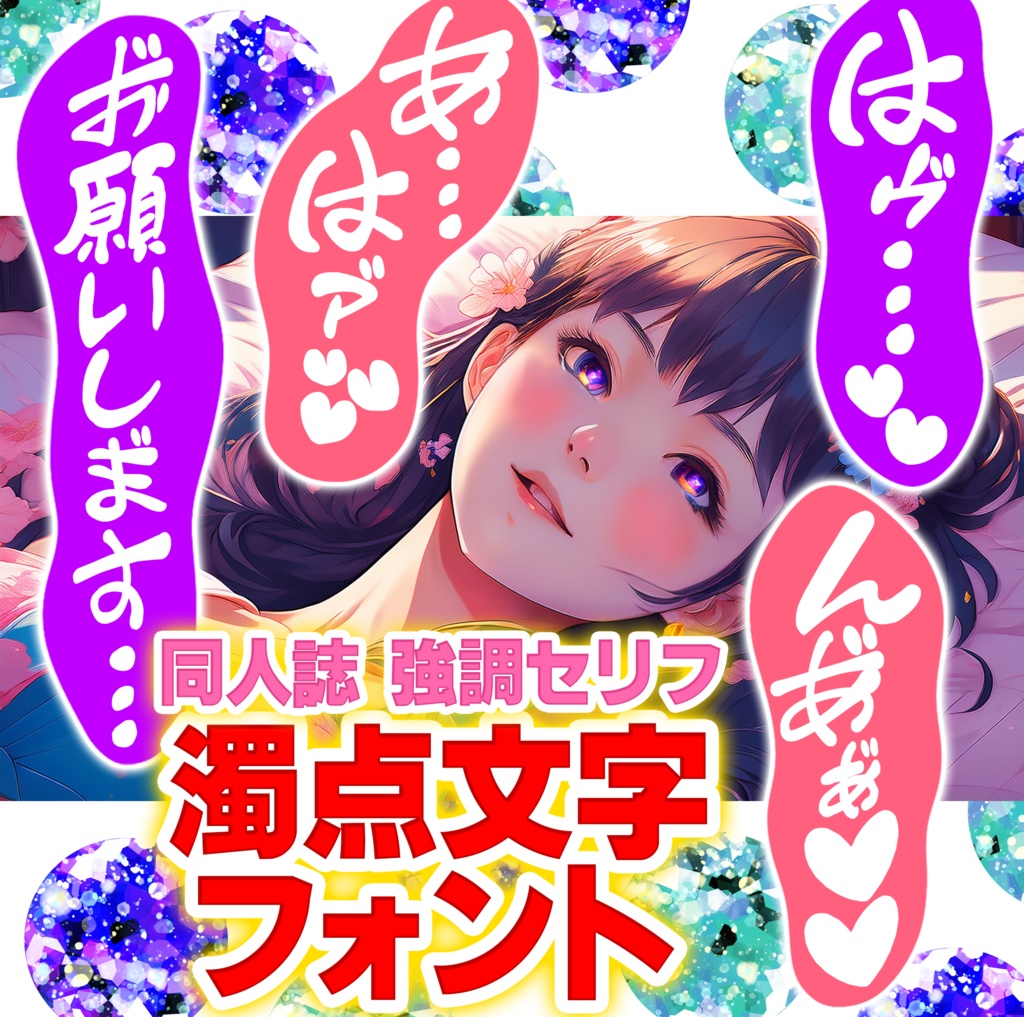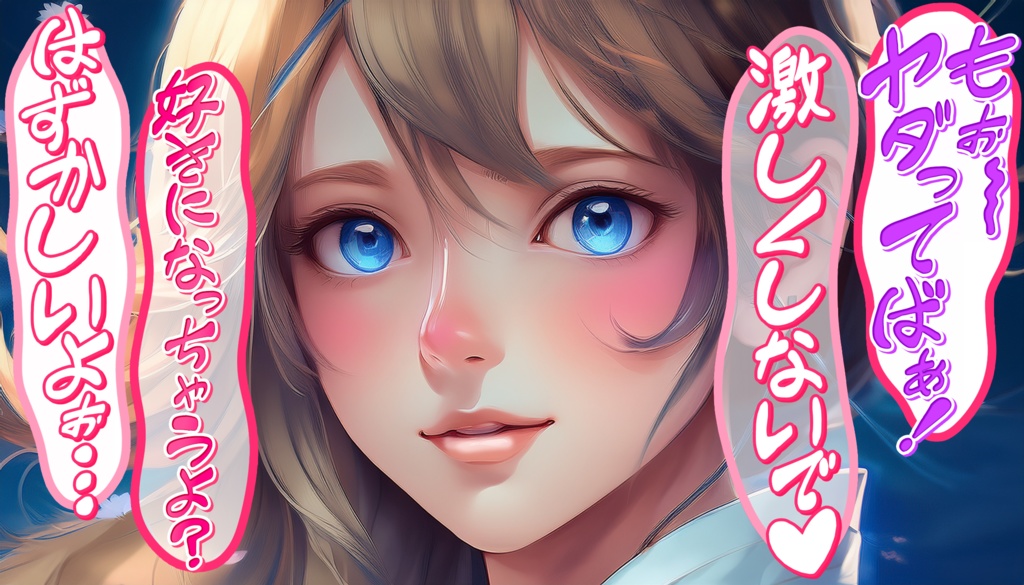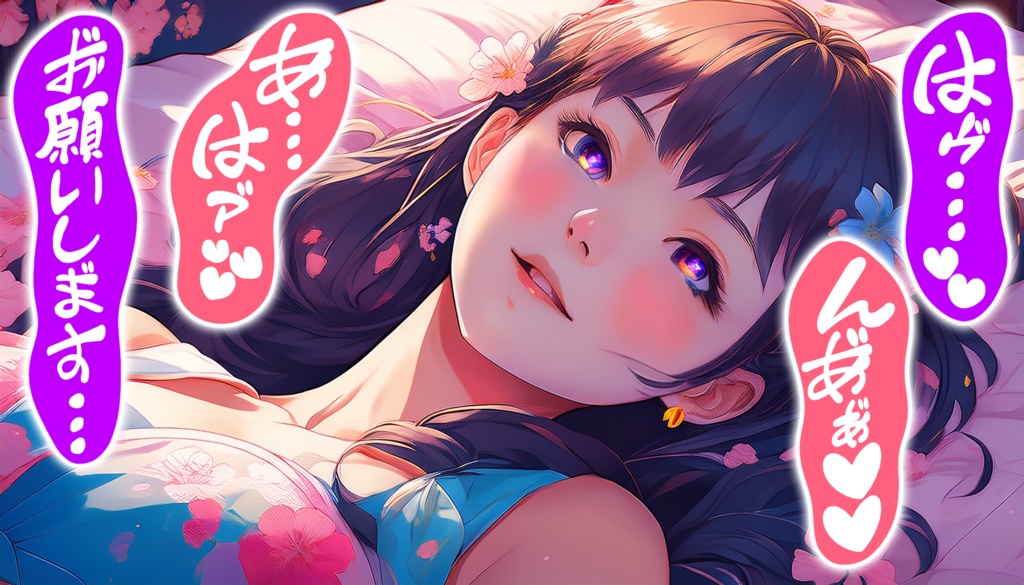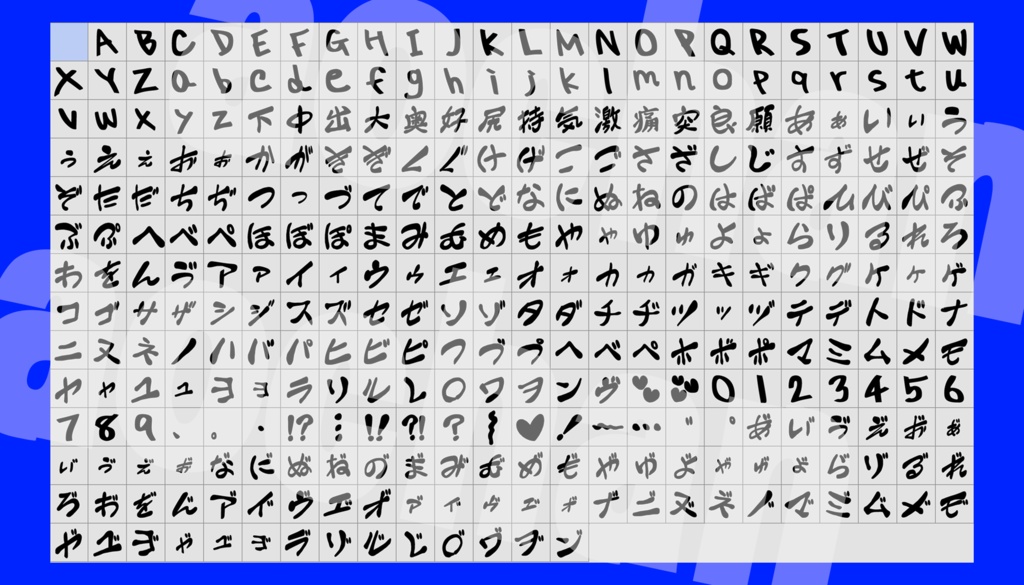
期間限定値下げ中★濁点つけ放題!同人誌 強調セリフ向け手書きフォント『aochan_odorimoji』
12月31日まで期間限定値下げ中! 濁点つけ放題!同人誌 強調セリフ用手書きフォント「aochan_odorimoji」 同人誌や創作漫画で使いやすい、手書き風の日本語フォントです。 特に「強調セリフ」「感情の爆発」「叫び」「崩れた語尾」などの表現に最適! 💥 特徴 通常は濁点が付かない文字にも濁点が付けられる「濁点つけ放題」 (例:「ぁ゛」「あ゛」「ん゛」「ア゛」など) ひらがな・カタカナ・アルファベット(大文字・小文字)・数字を収録 記号(♥ / ♥♥ / !? / !! / 〜 / …など)を収録 漢字は同人誌によく使用されるもののみ収録 収録内容は添付画像が全てです 💡 使用方法 キーボードからは「あ゛」などの濁点付き文字は入力できません。 文字一覧(字形)から選択して使用してください。 Photoshop:メニュー → ウィンドウ → 字形 から文字を選択 Illustrator:メニュー → 書式 → 字形 または ウィンドウ → 書式 → 字形 CLIP STUDIO PAINT(クリスタ):文字パレットを使用してください ✏ 収録内容 ひらがな・カタカナ アルファベット(大文字・小文字) 数字 記号(♥/ !? / ?! / !! / 〜 / …など) 漢字(同人誌によく使用されるもの) 濁点付き文字(あ゛・ん゛・ア゛など) 💼 商用利用について 個人・同人・商用利用すべてOK 再配布・自作発言は禁止 詳しくは同梱の利用規約をご確認ください 📦 同梱ファイル フォント本体(OTF形式) 利用規約.txt 簡単なインストール方法(Windows / Mac) 💌 最後に 強調セリフをもっと表情豊かにしたい方、 テンション高めの“あ゛”や“ん゛”がほしい方にぴったりのフォントです。 ぜひあなたの作品に使ってください!